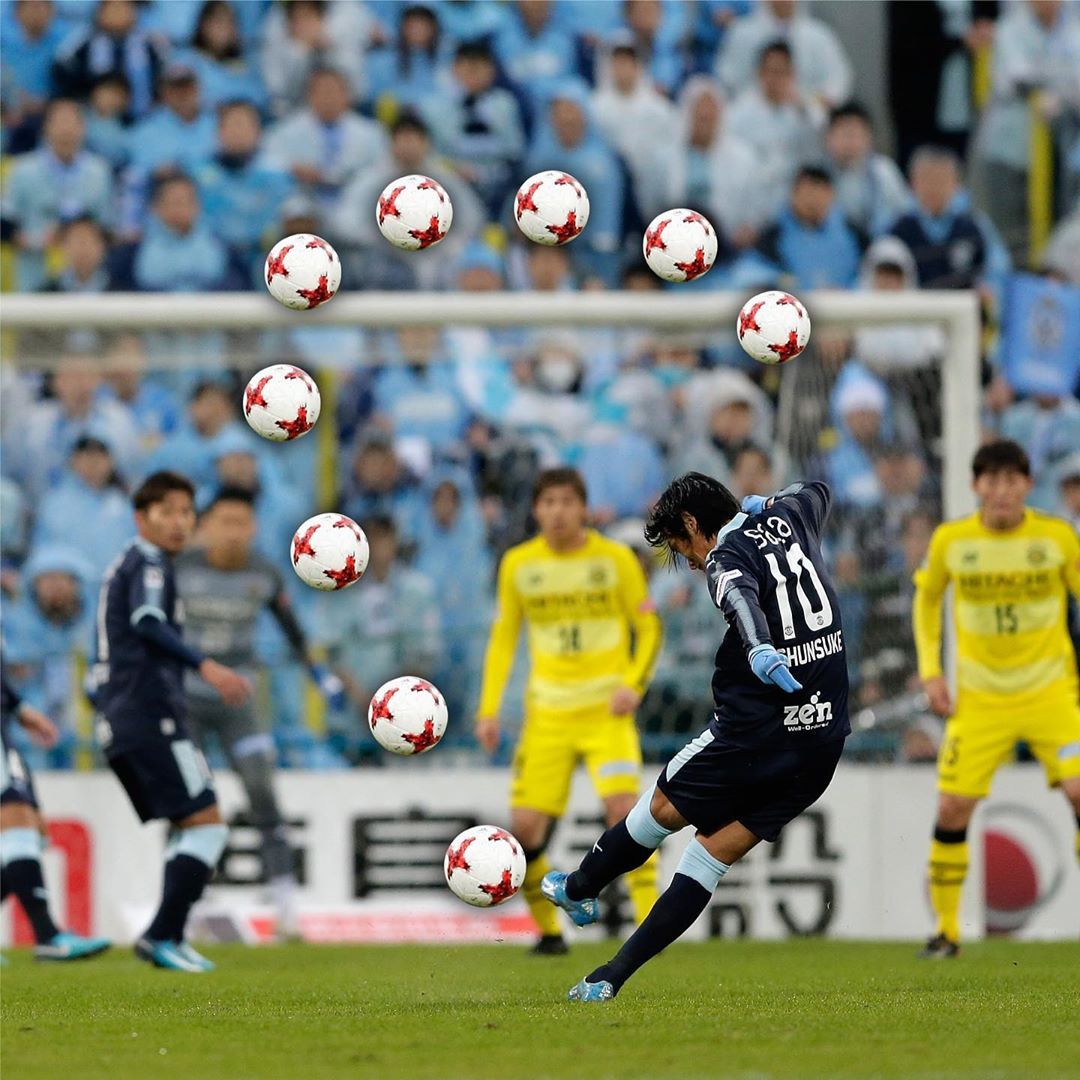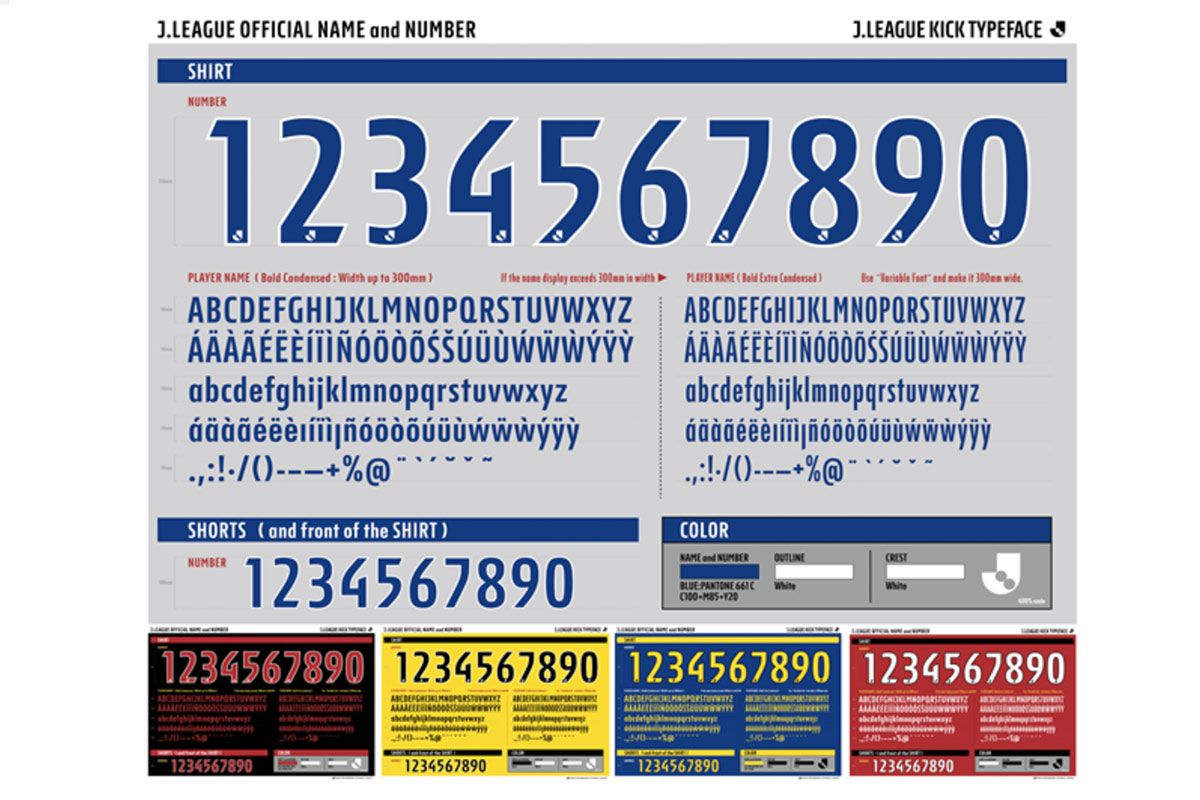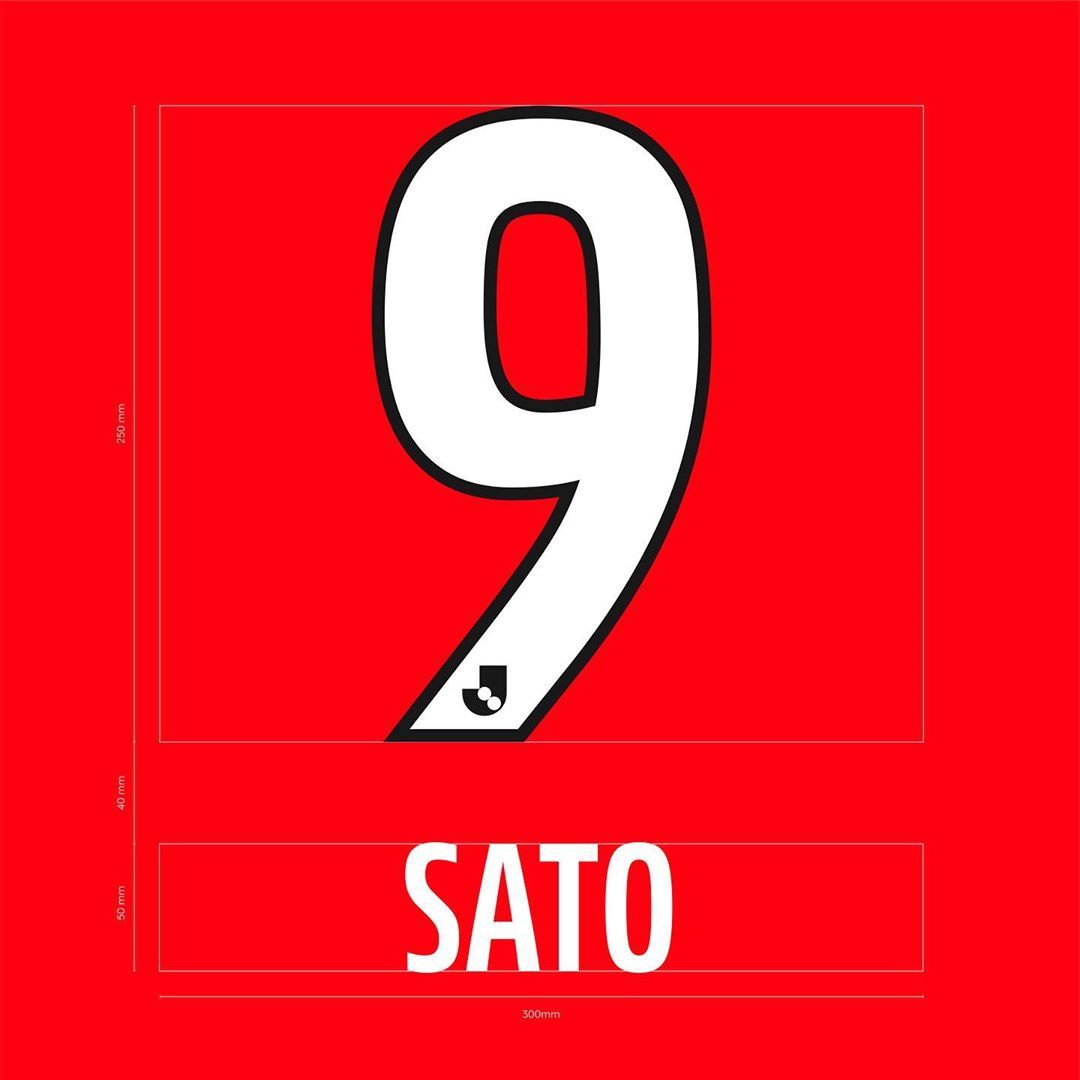
I nuovi font unici della J-League Un typeface ispirato al "tiro a giro"
Nell'ottica di un improvement dell'estetica della visibilità dei tornei, la J-League giapponese ha imposto un font type unico per tutti i club appartenenti alle sue competizioni: J1 League, J2 League, J3 League, League Cup, J1/J2 Play-Offs, Super Cup. Il nuovo typeface riguarderà sia i nomi che i numeri sul retro delle maglie e si chiamerà J-League Kick. I colori scelti per il nuovo carattere sono il rosso, il giallo, il blu, il nero e il bianco e sarà impostato sulle divise delle squadre a partire dalla stagione 2021, che in Giappone, dovrebbe iniziare il prossimo febbraio - attualmente è ancora in corso il torneo 2020.
Secondo gli organizzatori delle varie competizioni nipponiche, l'omogeneità dei font dovrebbe garantire una migliore qualità nella visione delle partite -soprattutto su smartphone e tablet, i nuovi device per seguire i match - e, allo stesso tempo, aumentare la visibilità del marchio J-League: la volontà infatti è di costruire un brand calcistico forte e attraente, e la strategia giapponese è quella di seguire alcune scelte viste anche in Europa, come ad esempio in Bundesliga, in Premier League, e da quest'anno anche in Serie A.
Il font è stato realizzato dallo studio di design danese Kontrapunkt, un'azienda leader nel settore grafico a livello internazionale. Il nuovo carattere della J-League è realizzato ispirandosi al 'tiro a giro', uno dei gesti sportivi più iconici di sempre e unione di stile, fisica e bravura tecnica. In sostanza, la sinuosità dei caratteri vorrebbe richiamare la traiettoria del tiro a giro così da evidenziare, insieme, la sua eleganza e abilità.